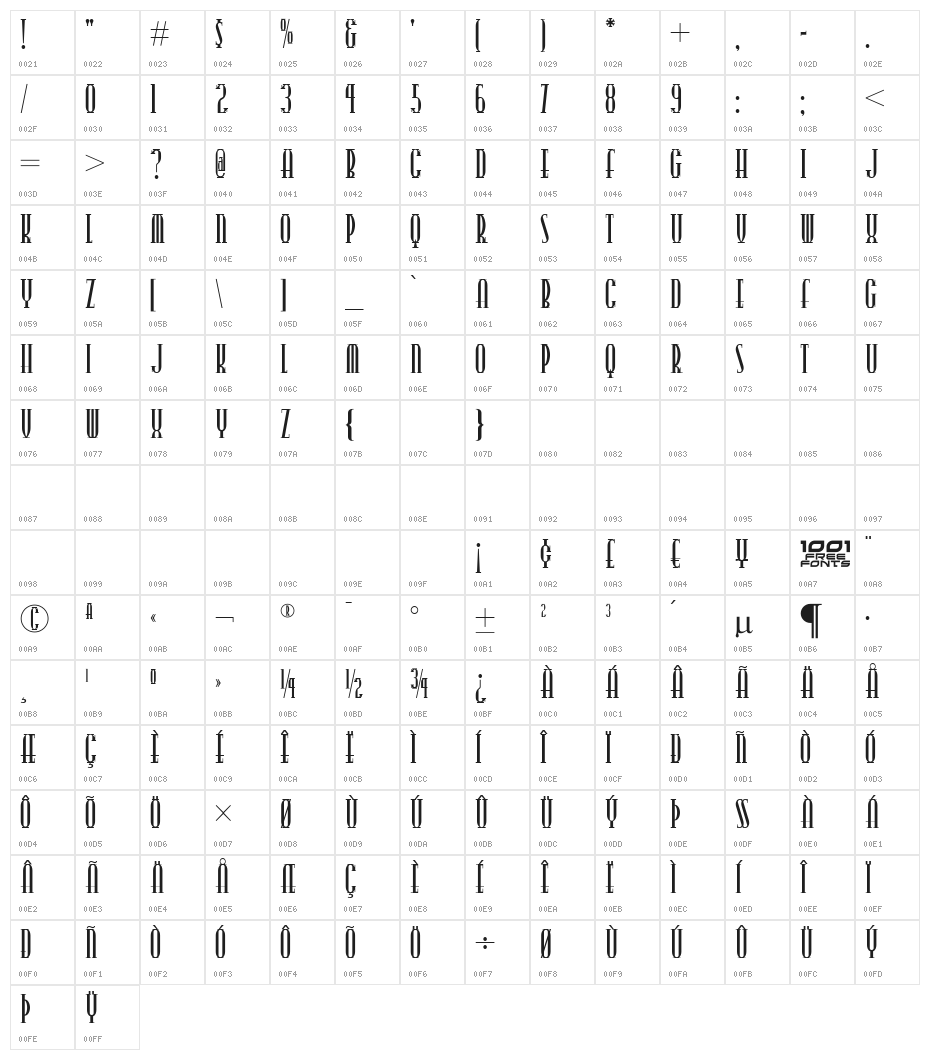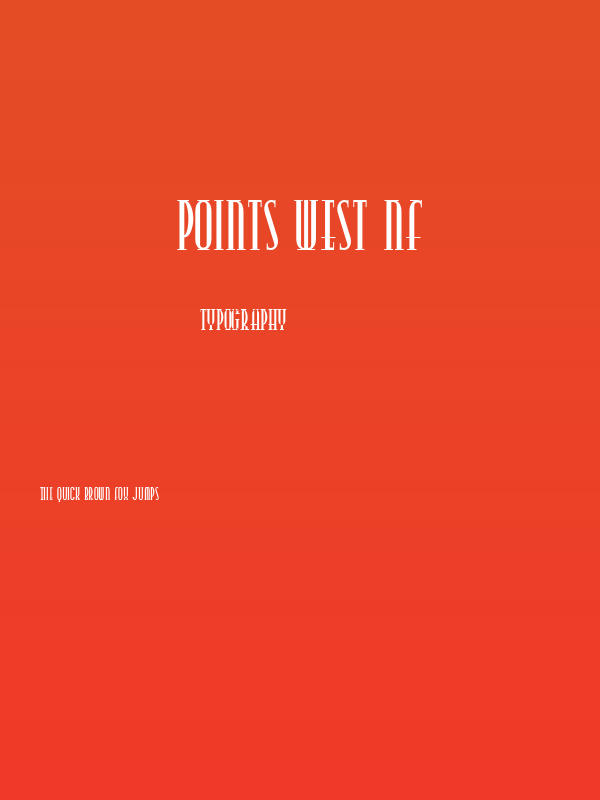
Points West NF Font
| العرض | Condensed |
| مشاريع مقترحة | Ideal for use in luxury branding, high-end fashion magazines, elegant invitations, and dramatic poster designs. |